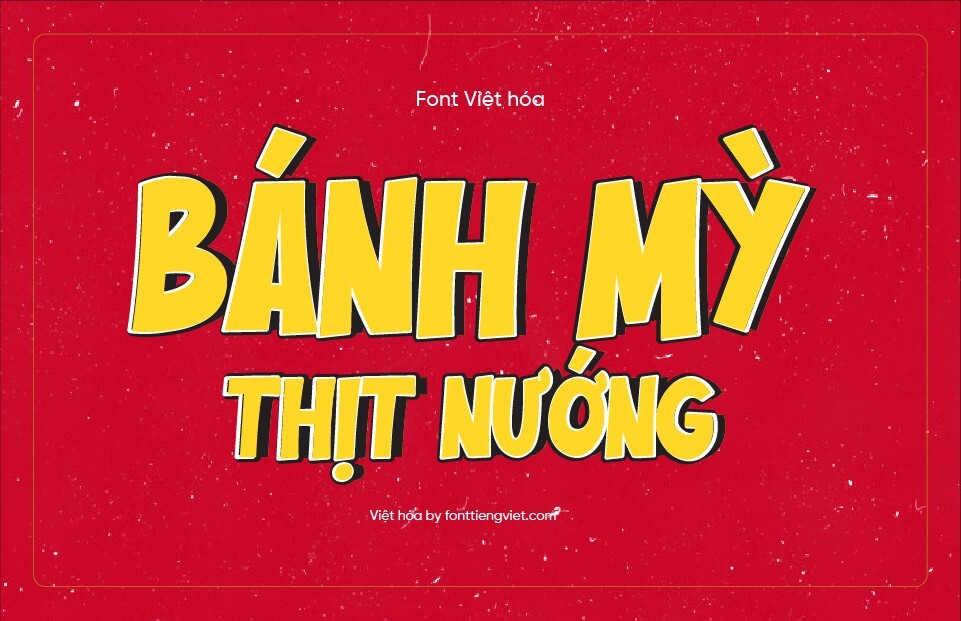
Font Việt hóa 1FTV VIP Bazinga!
Giới thiệu về Font Việt hóa 1FTV VIP Bazinga!
Trong thế giới thiết kế đồ họa dành cho học đường, việc lựa chọn một bộ Font Miễn Phí chất lượng luôn là ưu tiên hàng đầu của các thầy cô và học sinh. Font Việt hóa 1FTV VIP Bazinga! nổi lên như một giải pháp hoàn hảo nhờ phong cách thiết kế hiện đại, vui nhộn nhưng vẫn đảm bảo tính chuyên nghiệp. Đây là bộ font được tinh chỉnh kỹ lưỡng để phù hợp với bảng mã tiếng Việt, giúp người dùng dễ dàng tạo ra những ấn phẩm truyền thông bắt mắt mà không lo lỗi hiển thị hay thiếu dấu.
Đặc điểm nổi bật của bộ Font Việt hóa 1FTV VIP Bazinga!
Thiết kế độc đáo và linh hoạt
Font Việt hóa 1FTV VIP Bazinga! sở hữu các đường nét tròn trịa, mang lại cảm giác năng động và trẻ trung. Điều này cực kỳ phù hợp khi ứng dụng vào việc làm tiêu đề bài giảng, trang trí báo tường hoặc thiết kế poster sự kiện trường học. Độ dày của các ký tự được tính toán cân đối, giúp văn bản luôn rõ ràng dù ở kích thước lớn hay nhỏ. Ngoài ra, bộ font này còn hỗ trợ đầy đủ hệ thống dấu câu tiếng Việt theo chuẩn Unicode hiện nay.
Tính ứng dụng cao trong học tập
Không chỉ dừng lại ở các slide thuyết trình, Font Việt hóa 1FTV VIP Bazinga! còn được sử dụng rộng rãi trong việc làm thiệp chúc mừng, nhãn vở hoặc các video hoạt hình ngắn cho trẻ em. Sự thân thiện trong từng nét chữ giúp nội dung truyền tải trở nên gần gũi và dễ tiếp nhận hơn đối với người xem ở mọi lứa tuổi.